Gần đây, Font chữ Handwriting (chữ viết tay) khá phố biến trong thiết kế web vì những hiệu quả thiết kế mà nó mang lại. Hôm nay, Ngôi Sao Số Solutions xin giới thiệu với các bạn 24 Font chữ Handwriting đẹp đến từ nhiều nhà thiết kế trên khắp thế giới để các bạn tham khảo.
01. LeHand - Download Font
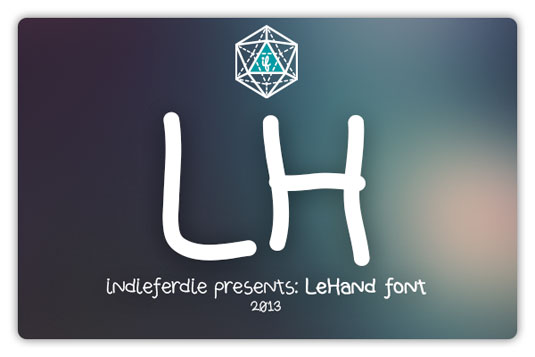
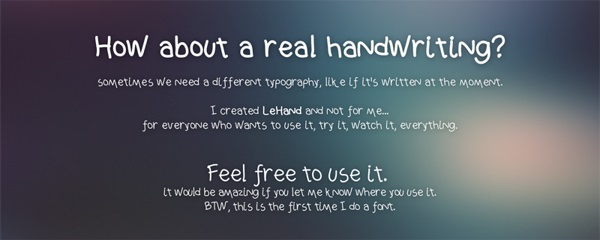
Font LeHand mang một phong cách khá vui tươi và sẽ khá tuyệt vời cho bạn để thử nghiệm với các dự án web mới. Là một nhà thiết kế web chuyên nghiệp, Ngôi Sao Số tin rằng LeHand sẽ đem đến nhiều cảm hứng trong việc thiết kế của bạn.
02. Yore - Download Font
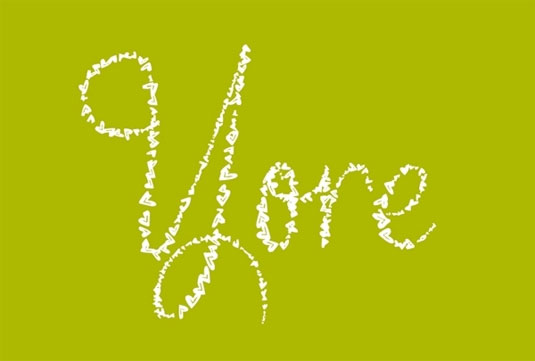
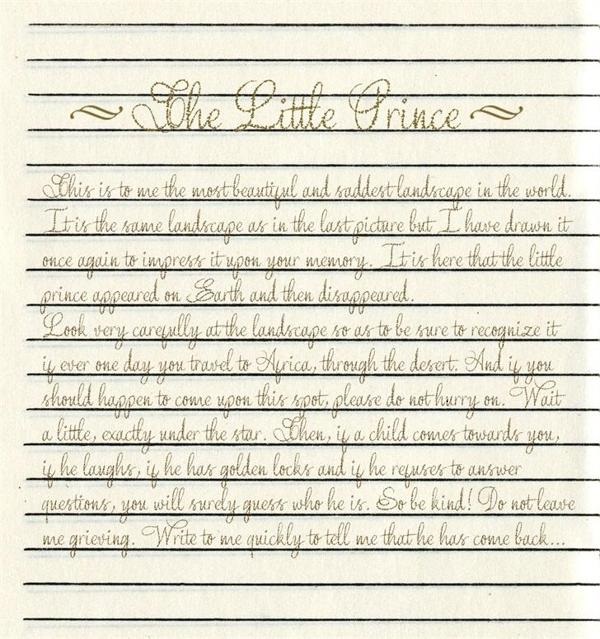
Yore được tạo ra bởi nhà thiết kế người Việt Nam Poem Haiku. Yore là một font chữ mang phong cách khá vui nhộn nhưng cũng khá truyền thống. Thật hoàn hảo nếu bạn sử dụng Yore cho phần thiết kế nội dung hay thiết kế bộ nhận diện thương hiệu.
03. Whatever it takes - Download Font
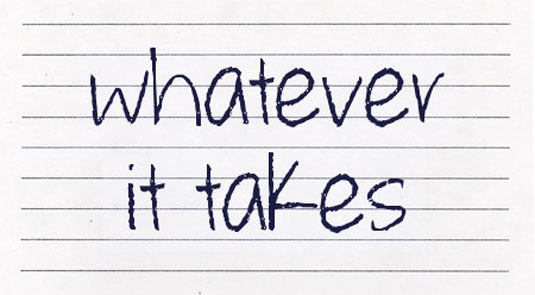
04. Before Breakfast - Download Font
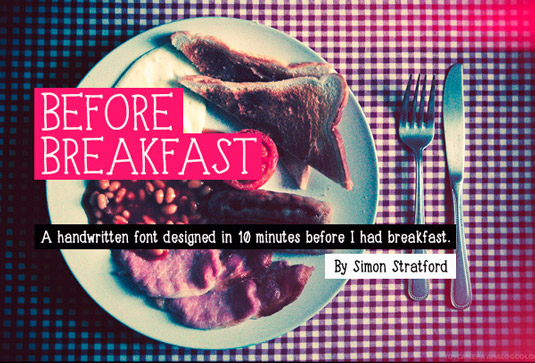
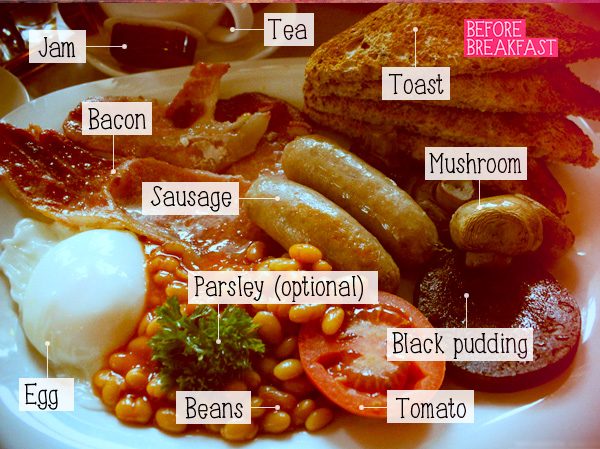
Gần đây nhà thiết kế Simon Stratford đã khám phá ra ứng dụng iFontMaker của iPad và ông đã thử tạo ra font chữ "Before Breakfast" trong chưa đầy 10'.
05. Engine- Download Font
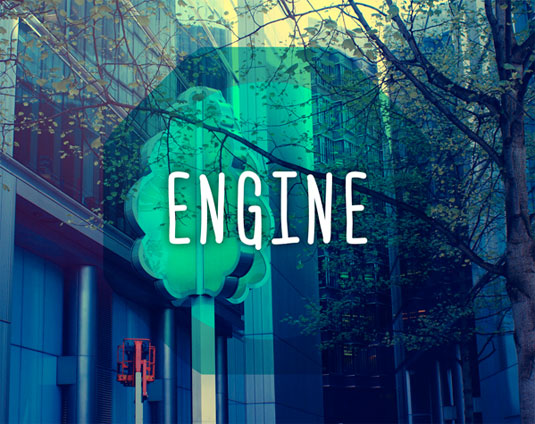
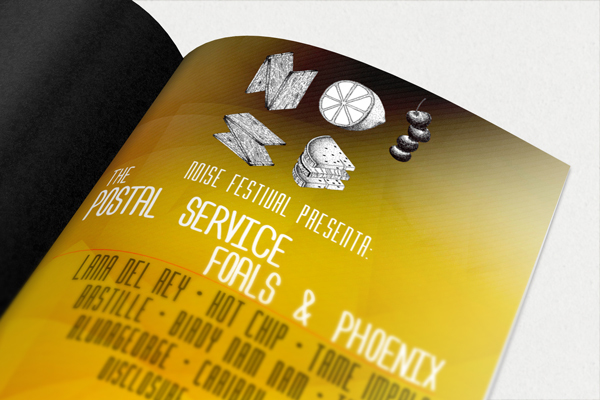
Có lẽ Engine là một trong những font chữ viết tay yêu thích của những nhà thiết kế chuyên nghiệp vì sự tiện dụng khi có thể ứng dụng cho nhiều ngôn ngữ khác nhau trong đó có tiếng Pháp, Tây Ban Nha, Ba Lan. Đây là thiết kế của Ferdie Balderas.
06. Chomp- Download Font
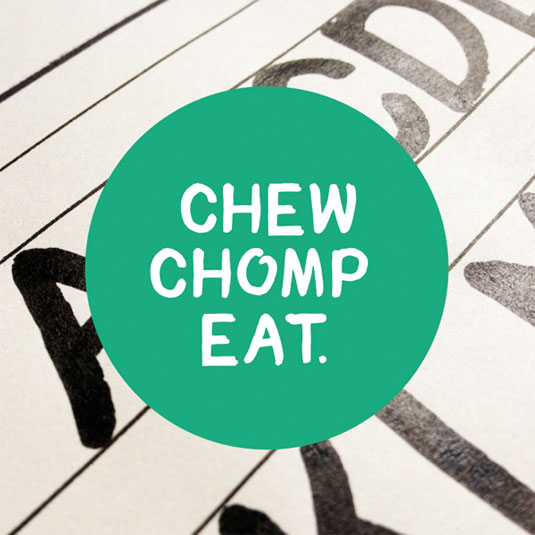
Đây là một font chữ vui nhộn được thiết kế bởi William Bayley Suckling. Là một sinh viên của đại học The London College of Communication, Suckling thường thử nghiệm và tạo ra những font chữ mới cho mọi người sử dụng.
07. LSTK Bembo - Download Font
Đây là một trong những font chữ viết tay đẹp và có tính ứng dụng cao, đặc biệt khi bạn muốn tạo ra một thiết kế vừa mang nét truyền thống vừa thể hiện cá tính cho web của bạn.
08. Haiku's Script - Download Font
Haiku là nỗ lực đầu tiên của Poem Haiku trong việc tạo ra font chữ. Phải mất 3 tháng từ tháng 7 đến tháng 9/2011 để nhà thiết kế tạo ra font chữ này.
09. Pops - Download Font
Pops được thiết kế dựa trên font chữ viết tay của cha nhà thiết kế, là font chữ thường được dùng để nhắn tin hay ghi các tiêu đề.
10. Sketch Block - Download Font
Font chữ này là thiết kế của Lukas Bischoff, nổi bật với các nét đậm nhưng sáng, thích hợp là font tiêu đề.
11. GoodDog - Download Font
Đây là thiết kế của Fonthead Design
12. J.D Handcrafted - Download Font